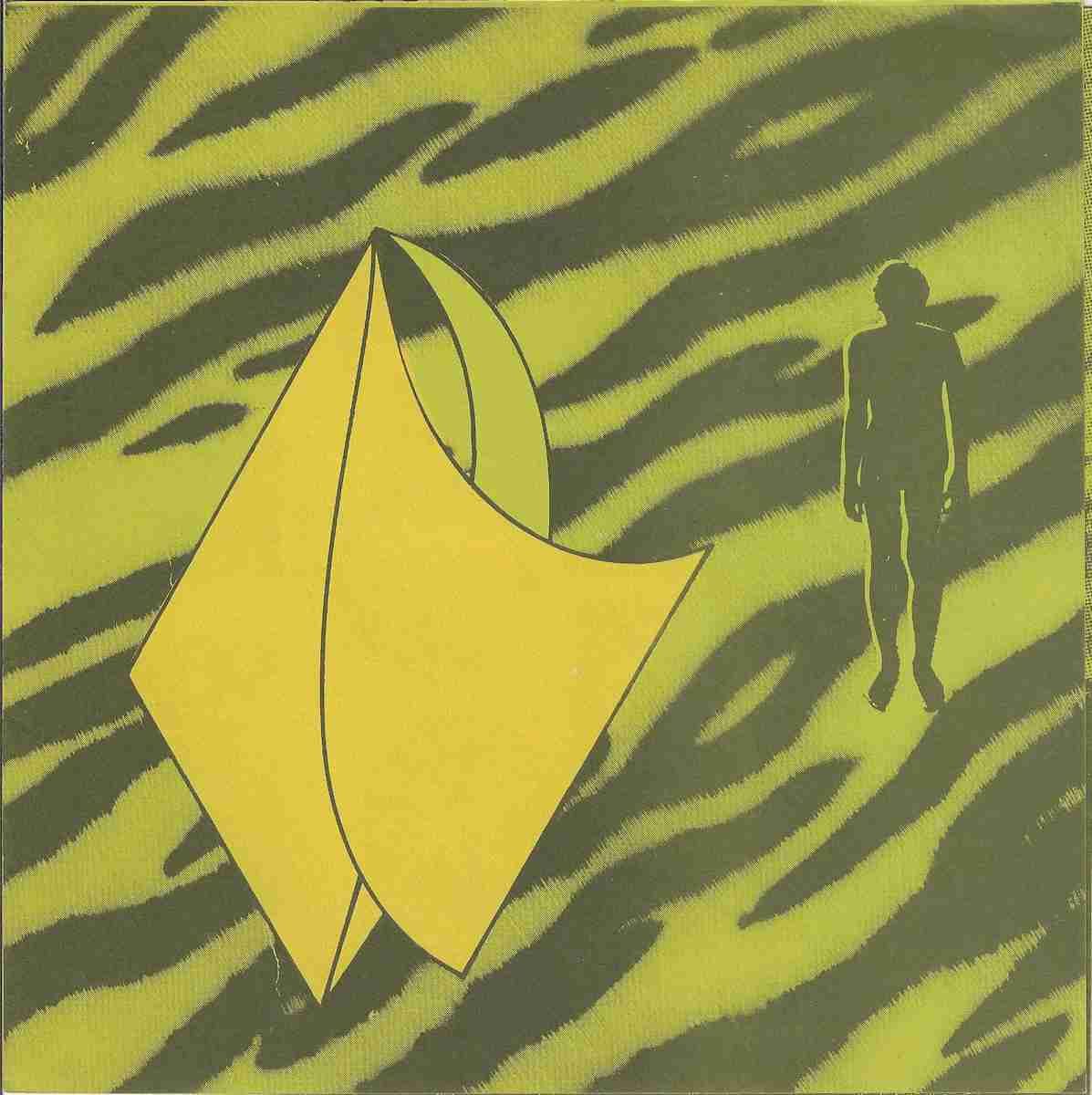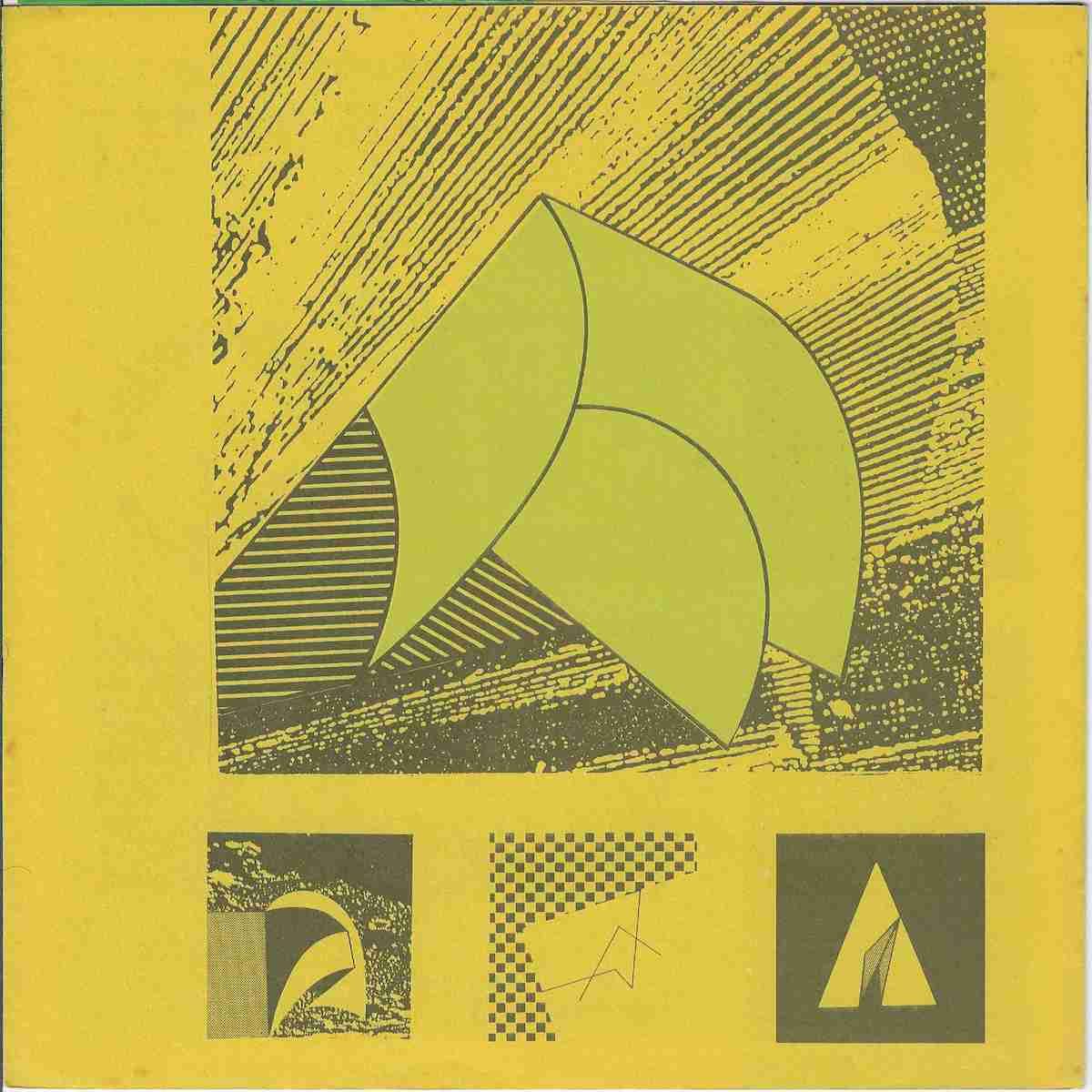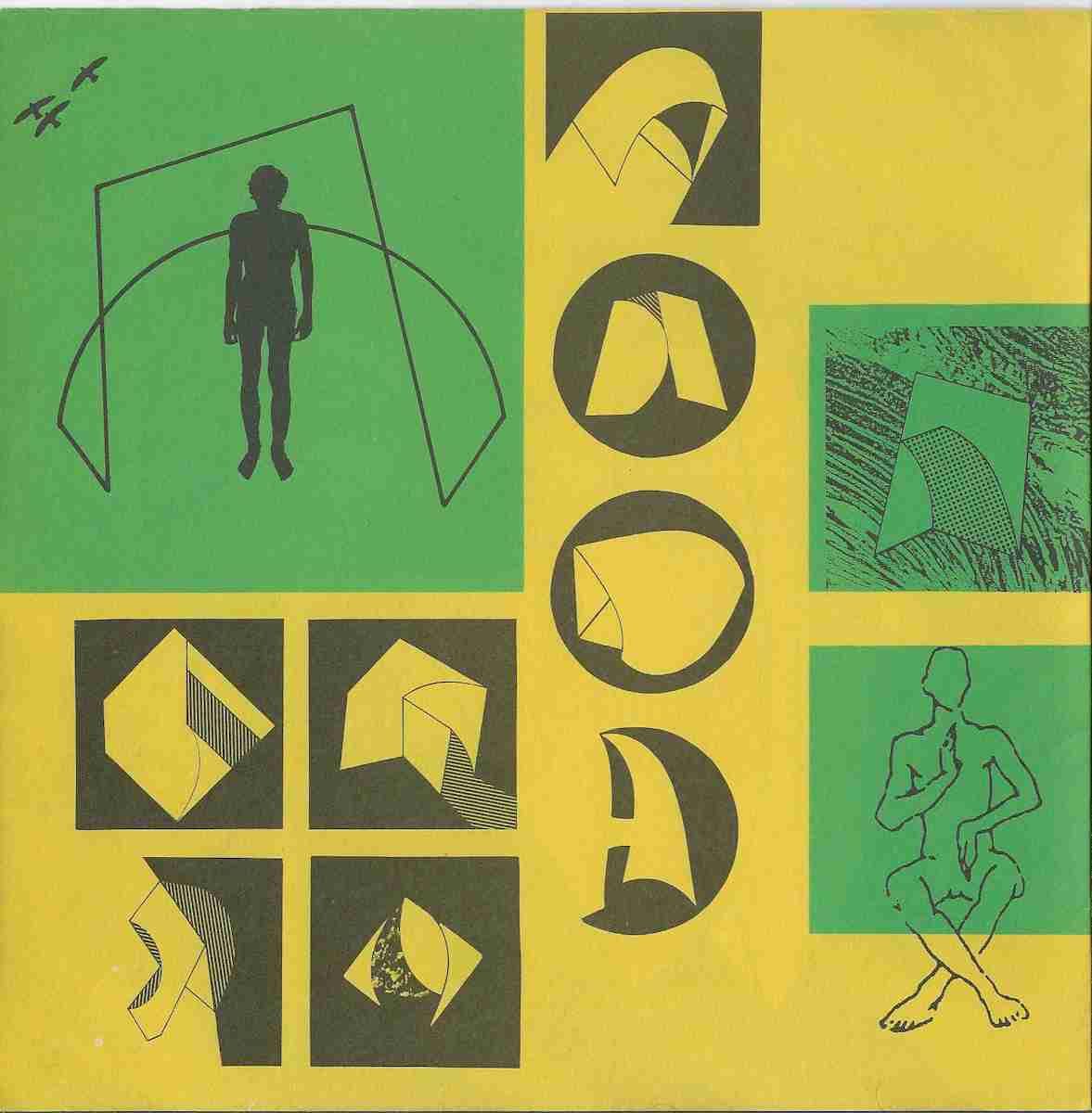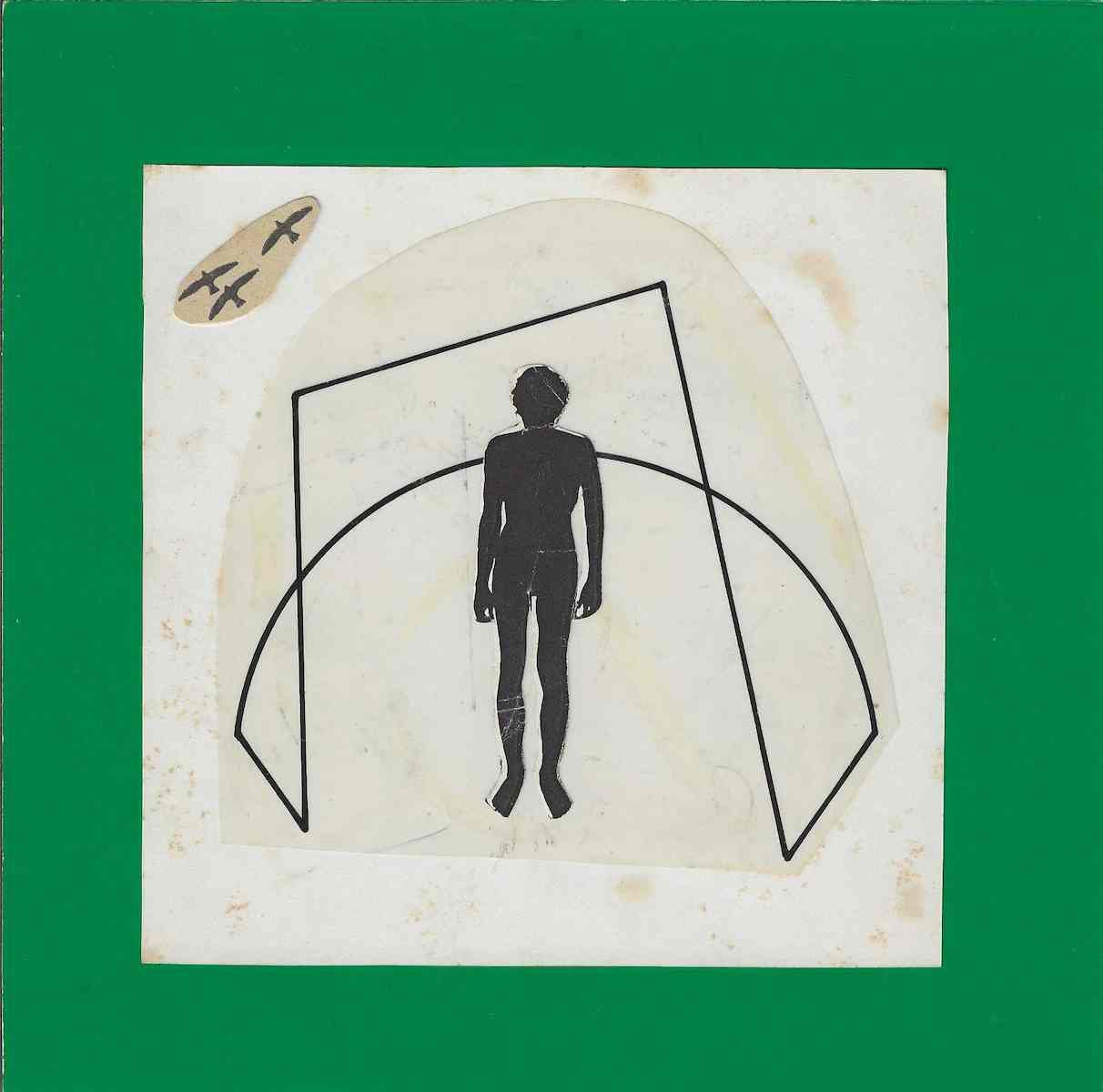
Wlademir Dias Pino, Política e Estética, 1994, publicação e conjunto gráfico relacionado à exposição realizada em 1994. O material articula texto biográfico, reflexão crítica, desenho, fotografia, composição gráfica, tipografia e estudos formais associados às pesquisas visuais do artista.
Wlademir Dias Pino
Texto para o programa SalsaWlademir Dias Pino, Política e Estética, 1994, publicação e conjunto gráfico relacionado à exposição realizada em 1994. O material articula texto biográfico, reflexão crítica, desenho, fotografia, composição gráfica, tipografia e estudos formais associados às pesquisas visuais do artista. A publicação apresenta texto de Maria de Arruda e situa a trajetória de Wlademir Dias Pino dentro de uma relação contínua entre experiência política, cultura gráfica, poesia, desenho e construção visual.O texto Política e Estética organiza a trajetória familiar e intelectual de Wlademir Dias Pino em diferentes tempos. Segundo a publicação, a história começa na Galícia, com a família Pino vinculada à atividade gráfica e envolvida em circunstâncias políticas. O jornal pertencente à família teria sido fechado oficialmente por questões políticas, levando à perseguição e à busca de asilo na Espanha. O texto menciona Ana Diaz Robles e registra posteriormente a passagem da família pela América, especialmente Buenos Aires e Rio de Janeiro.Em um segundo momento, já no Brasil, a família mantém ligação direta com a atividade gráfica. O texto registra a instalação de uma gráfica e a transferência para São Paulo, então importante centro industrial brasileiro. A atividade política, o ambiente operário e a cultura da impressão aparecem como componentes da formação histórica e cultural que antecede a produção de Wlademir Dias Pino.A publicação também relata a trajetória de Pepe, irmão de sua mãe, ligado ao teatro e à atividade política, mencionando sua atuação durante a Revolução Paulista e posteriormente no jornalismo no Rio de Janeiro. É nesse ambiente de imprensa, gráfica e comunicação que nasce Wlademir Dias Pino. O texto destaca que ele cresce cercado por tipos gráficos e aprende a ler praticamente ao mesmo tempo em que começa a falar. Sua mãe, Laura, teria utilizado os próprios jornais editados pelo marido para ensiná lo a ler. Essa formação é apresentada como uma possível origem de sua radical relação entre palavra, imagem, tipografia e estrutura visual.O texto menciona ainda as pesquisas desenvolvidas posteriormente por Wlademir Dias Pino no Laboratório de Pesquisas Visuais, onde teria criado aproximadamente quinhentos alfabetos com a intenção de selecionar uma tipologia adequada à UEMT, demonstrando a continuidade de sua investigação sobre sistemas gráficos, alfabetos, leitura, design e comunicação visual.No quarto tempo do texto, Maria de Arruda relaciona diretamente essas experiências à exposição realizada em 1994. A autora observa que Wlademir Dias Pino apresenta uma proposta diferente daquela desenvolvida anteriormente no lançamento de A Ave e retoma sua afirmação de que o poema pode ser realizado sem palavras. O texto associa a exposição a uma investigação do fóssil de um rótulo, à ideia de vibração e a uma malha de ginástica, transformando A Ave em objeto escultórico e em uma espécie de cena teatral. As letras deixam de funcionar apenas como signos desenhados e passam a constituir planos não frontais, aproximando escrita, objeto, espaço e escultura.As imagens reproduzidas na publicação reforçam esse pensamento. Formas curvas e angulares aparecem como estruturas abertas, dobradas e projetadas no espaço. Figuras humanas são utilizadas como referência de escala e de relação corporal com essas construções. Fotografias, desenhos e montagens mostram diferentes possibilidades de transformação de uma mesma matriz formal. A página gráfica funciona como campo experimental no qual arquitetura, escultura, letra, corpo, fotografia e desenho se relacionam.Política e Estética constitui assim documento relevante para compreender a obra de Wlademir Dias Pino em 1994 e suas conexões com o Poema Processo, a poesia visual brasileira, a comunicação visual, a tipografia experimental, o design gráfico, o livro de artista, a arte conceitual e as pesquisas sobre sistemas de leitura. O documento também evidencia a permanência de A Ave como uma das matrizes fundamentais de sua produção e sua transformação posterior em estruturas espaciais, objetos e experiências próximas da escultura.Text for the Salsa programWlademir Dias Pino, Politics and Aesthetics, 1994, is a graphic publication and visual ensemble associated with an exhibition held in 1994. The material combines biographical writing, critical reflection, drawing, photography, graphic composition, typography and formal studies connected with the visual research developed by the artist. The publication includes a text by Maria de Arruda and places the trajectory of Wlademir Dias Pino within a continuous relationship between political experience, print culture, poetry, drawing and visual construction.The text Politics and Aesthetics organizes the family and intellectual history of Wlademir Dias Pino into different periods. According to the publication, the story begins in Galicia, where the Pino family was connected with printing activities and affected by political circumstances. A newspaper owned by the family was officially closed for political reasons, resulting in persecution and the search for asylum in Spain. The text mentions Ana Diaz Robles and later records the movement of the family through the Americas, particularly Buenos Aires and Rio de Janeiro.In a second period, already in Brazil, the family maintained a direct connection with the printing trade. The text records the establishment of a printing house and the move to São Paulo, then an important Brazilian industrial center. Political activity, the working class environment and print culture appear as components of the historical and cultural background preceding the artistic production of Wlademir Dias Pino.The publication also recounts the trajectory of Pepe, the brother of his mother, connected with theater and political activity, mentioning his participation during the Paulista Revolution and his later journalistic work in Rio de Janeiro. Wlademir Dias Pino was born within this environment of journalism, printing and communication. The text emphasizes that he grew up surrounded by printing types and learned to read almost at the same time that he began to speak. His mother Laura reportedly taught him to read through newspapers edited by her husband. This formative environment is presented as a possible origin of his radical relationship between word, image, typography and visual structure.The text also refers to research later conducted by Wlademir Dias Pino at the Laboratory of Visual Research, where he reportedly created approximately five hundred alphabets in order to select a typology appropriate to UEMT, demonstrating the continuity of his investigation into graphic systems, alphabets, reading, design and visual communication.In the fourth period of the text, Maria de Arruda directly connects these experiences with the exhibition presented in 1994. She observes that Wlademir Dias Pino introduces a proposal different from the one developed earlier with the launch of A Ave and recalls his statement that a poem can be produced without words. The text relates the exhibition to an investigation involving the fossil of a label, the idea of vibration and a gymnastics mesh, transforming A Ave into a sculptural object and a kind of theatrical scene. Letters no longer function only as drawn signs and instead become non frontal planes, bringing writing, object, space and sculpture into the same field.The images reproduced in the publication reinforce this approach. Curved and angular forms appear as open structures, folded and projected into space. Human figures are used as references of scale and bodily relationship with these constructions. Photographs, drawings and montages demonstrate different possibilities for transforming the same formal matrix. The graphic page becomes an experimental field in which architecture, sculpture, letter, body, photography and drawing interact.Politics and Aesthetics is therefore an important document for understanding the work of Wlademir Dias Pino in 1994 and its connections with Poema Processo, Brazilian visual poetry, visual communication, experimental typography, graphic design, artist books, conceptual art and research into systems of reading. The document also demonstrates the continued importance of A Ave as one of the fundamental matrices of his production and its later transformation into spatial structures, objects and experiments approaching sculpture.
Texto de observaçãoMaterial gráfico de Wlademir Dias Pino identificado como Política e Estética, datado de 1994. O conjunto é composto por páginas impressas em amarelo, verde e preto, contendo composições gráficas, desenhos, fotografias, estudos de formas tridimensionais e texto de Maria de Arruda. O texto apresenta aspectos da história familiar do artista, destacando a origem galega da família Pino, sua ligação com gráficas, jornais, política e atividade intelectual, além da formação precoce de Wlademir Dias Pino no ambiente tipográfico.O documento registra também sua pesquisa com alfabetos no Laboratório de Pesquisas Visuais e estabelece relação entre essa trajetória e a exposição de 1994. Maria de Arruda destaca a transformação de A Ave em objeto escultórico e cena espacial, observando que as letras passam a funcionar como planos e estruturas não frontais. As imagens apresentam formas geométricas e orgânicas em diferentes configurações, algumas acompanhadas de figuras humanas que indicam escala e sugerem relação direta entre corpo, objeto e espaço.Documento de interesse para pesquisas sobre Wlademir Dias Pino, A Ave, Poema Processo, poesia visual, poesia experimental brasileira, tipografia, alfabetos visuais, comunicação visual, design gráfico, arte conceitual, objeto, escultura, livro de artista, Laboratório de Pesquisas Visuais, Maria de Arruda e arte brasileira da década de 1990Observation textGraphic material by Wlademir Dias Pino identified as Politics and Aesthetics and dated 1994. The ensemble consists of printed pages using yellow, green and black, containing graphic compositions, drawings, photographs, studies of three dimensional forms and a text by Maria de Arruda. The text presents elements of the family history of the artist, emphasizing the Galician origins of the Pino family and its connections with printing houses, newspapers, politics and intellectual activity, as well as the early formation of Wlademir Dias Pino within a typographic environment.The document also records his research with alphabets at the Laboratory of Visual Research and establishes a relationship between this trajectory and the 1994 exhibition. Maria de Arruda emphasizes the transformation of A Ave into a sculptural object and spatial scene, noting that letters begin to operate as planes and non frontal structures. The images present geometric and organic forms in several configurations, some accompanied by human figures that indicate scale and suggest a direct relationship between body, object and space.Document relevant to research on Wlademir Dias Pino, A Ave, Poema Processo, visual poetry, Brazilian experimental poetry, typography, visual alphabets, visual communication, graphic design, conceptual art, objects, sculpture, artist books, Laboratory of Visual Research, Maria de Arruda and Brazilian art of the 1990s.
Wlademir Dias Pino, Politics and Aesthetics, 1994, is a graphic publication and visual ensemble associated with an exhibition held in 1994. The material combines biographical writing, critical reflection, drawing, photography, graphic composition, typography and formal studies connected with the visual research developed by the artist.